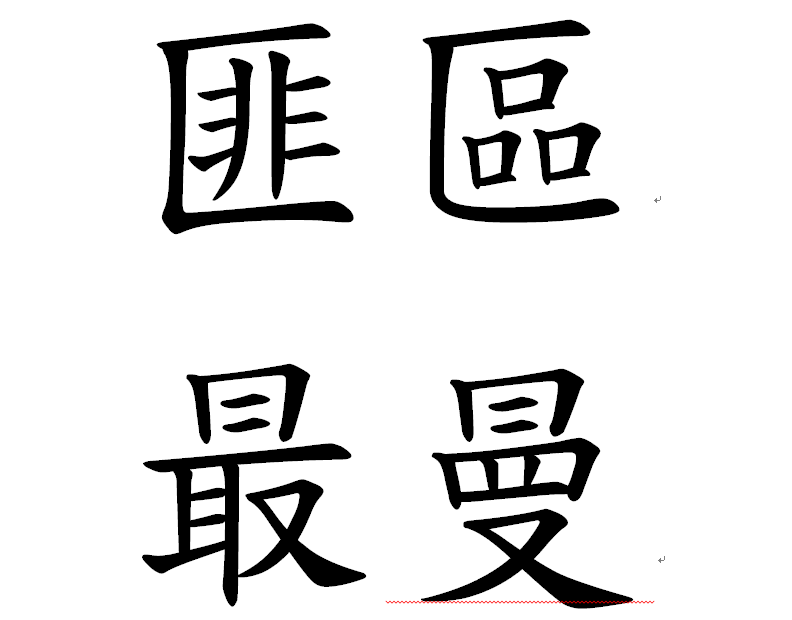
根據「常用標準國字字體」規範,下列字形寫法的敘述,何者正確?
(A)「舌」字第一筆與「活」字第四筆寫法相同。
(B)「曼」字與「最」字上面部分寫法相同。
(C)「廷」字右邊與「任」字右邊寫法相同。
(D)「匪」字左邊與「區」字左邊寫法相同。
舌:一橫
活;一撇
曼:又部
最:冂(ㄐㄩㄥ)部
廷:一撇
任:一橫
匪:匚(ㄈㄤ)部
區:匚(ㄒㄧˋ)部
匚(ㄒㄧˇ) 部  是唸三聲哦
匸ㄒㄧˋ